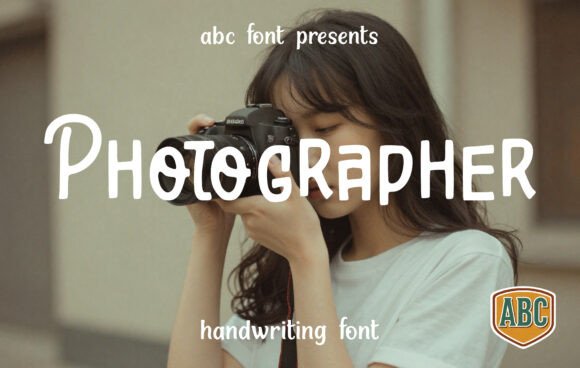
Photographer
Encontrar los elementos de diseño adecuados puede ser un desafío, pero Photographer ofrece una colección excepcional que eleva tu trabajo al instante.
Elaborado con precisión, Photographer proporciona vectores limpios, tipografía suave y una licencia comercial para tu tranquilidad.